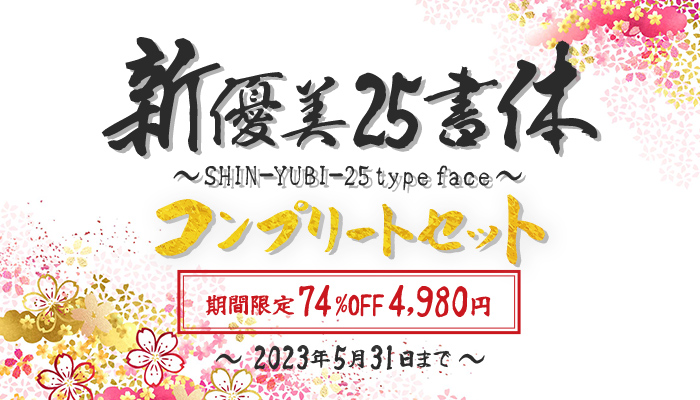
新優美25書体コンプリートセット
個性的な手書きフォントから優雅で美しい毛筆フォントまで、多数の書家の多彩なフォントを取りそろえるスキルインフォメーションズから、使い勝手の良い筆書体「優美書体」に、おしゃれな印象を与える「板書体」や「鳳書体」「相撲甚句」の筆書体、繊細で読みやすい「新優美ペン字体」の新書体を追加した「新優美25書体コンプリートセット」を2026年3月31日までの期間限定 4,980円の特別価格でご提供いたします。
「新優美25書体コンプリートセット」は、使い勝手の良い筆書体として親しまれ15書体のラインナップを展開していた「優美書体」シリーズに、新たに追加された汎用性が高くおしゃれな印象を与える10書体を含む、全25書体を収録したお得なセット商品です。
新優美25書体コンプリートセット 使用例
優美太板書R・糸巻楷書
新優美25書体コンプリートセット 使用例
優美ペンR・優美ペン行書・優美太筆R
新優美25書体コンプリートセット 使用例
1. TAS-新優美ペン字行書
TAS-新優美ペン字行書
2. TAS-新優美ペン字楷書
TAS-新優美ペン字楷書
3. TAS-新優美板書
TAS-新優美板書
4. TAS-優美板書行書
TAS-優美板書行書
5. TAS-優美板書楷書
TAS-優美板書楷書
6. TAS-糸巻楷書
TAS-糸巻楷書
7. TAS-鳳書体
TAS-鳳書体
8. TAS-新優美毛筆行書
TAS-新優美毛筆行書
9. TAS-新優美毛筆楷書
TAS-新優美毛筆楷書
10. TAS-新優美相撲甚句
TAS-新優美相撲甚句
11. TAS-優美筆RM
TAS-優美筆RM
12. TAS-優美太筆R
TAS-優美太筆R
13. TAS-優美ペンR
TAS-優美ペンR
14. TAS-優美ペン極細R
TAS-優美ペン極細R
15. TAS-優美板書R
TAS-優美板書R
16. TAS-優美太板書R
TAS-優美太板書R
17. TAS-優美筆行書